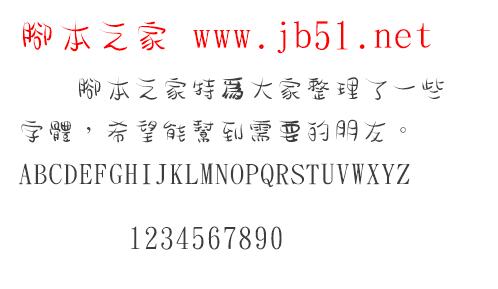
金梅浪漫飘洒字体 繁体
金梅浪漫飘洒字体是一款潇洒飘逸的艺术字体,该字体如它的名字一般,书写非常流畅飘逸,具有不拘一格的风格,整体看上去有强烈的视觉冲击力,可以很好的应用于文本装潢、信息展示、网页设计、篆刻制模、数据制作、装潢设计、计算艺术设计、视觉设计、字帖等一切合法应用场景,有喜欢的朋友可免费下载收藏。